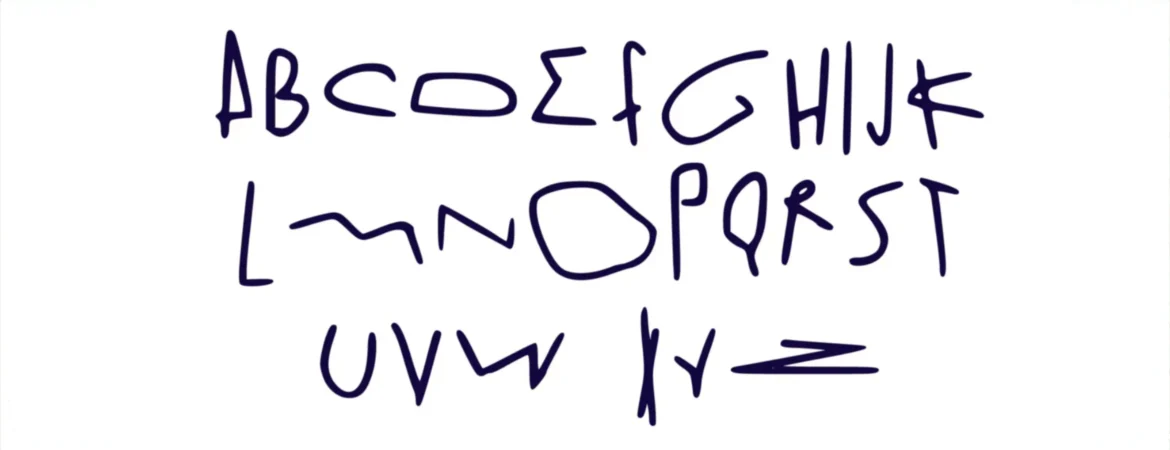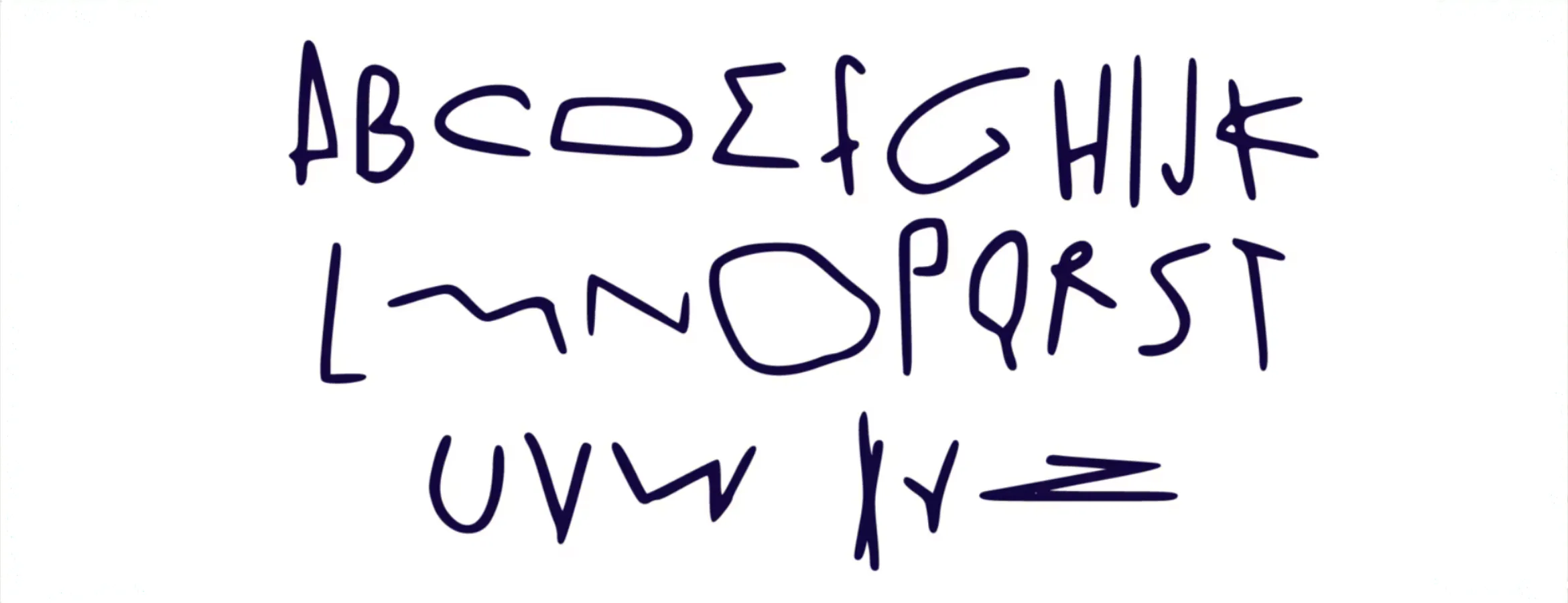
Des lettres qui se jouent sur le terrain.
Pour rendre hommage à Lionel Messi après son annonce de retraite de la sélection argentine, Rexona Argentine dévoile GOAT Font, une typographie dont chaque lettre est directement inspirée d’une action du joueur sous le maillot de l’Albiceleste. Révélée sur Instagram, cette campagne transforme dribbles, passes et tirs du footballeur en une police.
Le principe est plutôt simple : chaque lettre de l’alphabet correspond à un mouvement précis réalisé par Messi sur le terrain. Rexona s’intéresse à ce qui a fait la particularité du joueur pendant vingt ans : ses déplacements et ses trajectoires. Les formes obtenues composent une véritable police de caractères.
Rexona n’a indiqué ni les matchs dont sont tirées les différentes actions, ni la méthode utilisée pour transformer ces mouvements en lettres. Aux fans de se plonger dans les archives vidéo pour tenter de retrouver le match et l’action correspondant à chaque caractère. La typographie devient alors autant un hommage à Messi qu’un petit jeu de piste pour ceux qui connaissent les gestes du joueur par cœur.
Disponible gratuitement sur le site argentin de Rexona, GOAT Font peut ensuite être utilisée pour créer ses propres visuels. Une manière pour la marque de prolonger l’hommage au-delà de l’annonce de la retraite internationale de Messi, en laissant aux supporters un objet avec lequel continuer à écrire autour de sa carrière.